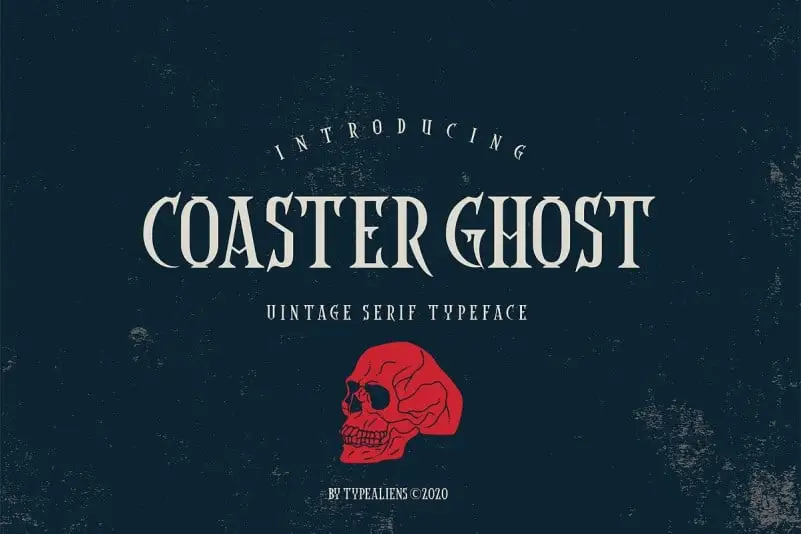
Coaster Ghost Vintage Font – Download Grátis
Introduzimos Coaster Ghost Vintage Font, uma tipografia serifada clássica com toque moderno. Esta tipografia versátil é perfeita para masthead e pull quotes, bem como logos de marca. Ela foi criada por ilhamtaro. Essa fonte serifada possui um estilo rígido adequado tanto para a criação de estílbis quanto para o design de logomarca, título ou fonte auxiliar. O impressiono da rigidez desta fonte deixa-a com uma aparição que é, sem sombra de dúvidas, um pouco gótica e claramente vintage. Ideal tanto para designers de estílbis quanto para aqueles trabalhando em logomarcas, Coaster Ghost Vintage Font será certamente uma opção popular entre os amantes da tipografia vintage modernizada.